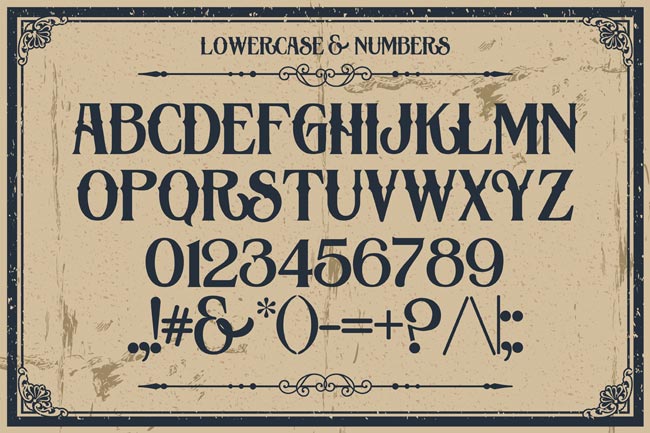
Лучшие ретро-шрифты для совершенствования вашего дизайнаDesigne-R
В этом посте мы представляем вам коллекцию высококачественных винтажных и лучших ретро-шрифтов, чтобы добавить нотку ностальгии в вашу работу.
При создании дизайна под влиянием искусства и культуры определенной эпохи лучше всего выбирать шрифты, которые визуально представляют этот период времени. Вот почему мы включили шрифты, вдохновленные эстетикой разных времен, будь то классический стиль начала 1900-х годов, стиль поп-арта 50-х и 60-х годов или фильмы, музыка и визуальные эффекты 70-х и 80-х годов. все!
Вы найдете сочетание различных стилей шрифтов, от шрифтов в стиле ретро до шрифтов кисти, жирных шрифтов с заглавными буквами до узких сжатых шрифтов, от монолинейных сценариев до многострочных шрифтов, пиксельных шрифтов, старинных шрифтов и многого другого. Эти шрифты идеально подходят для ваших проектов в винтажном и ретро-стиле, таких как флаеры, баннеры, приглашения, футболки, плакаты и дизайн логотипов.
В нашей коллекции есть как бесплатные, так и платные шрифты, и мы поместили их в разные разделы для удобства просмотра. В последнее время в моде ретро-дизайн 80-х и 90-х годов, ниже вы найдете довольно хороший выбор шрифтов, на которые повлияли стили шрифтов этих знаковых десятилетий.
Бесплатные винтажные и ретро шрифты
1. Streetwear – Бесплатный ретро Script шрифт
Streetwear – это смелый и стильный шрифт в стиле ретро, подходящий для логотипов, плакатов, брендинга, упаковки и футболок.
Он выглядит как шрифт 1960-х и 70-х годов, связанный с модой и спортом, уникальный и забавный одновременно.
Вы можете получить доступ к альтернативным персонажам Streetwear с помощью продвинутых программ OpenType, таких как Adobe Illustrator и InDesign. Дизайн студии Artimasa.
2. Sabo – Бесплатный Пиксельный шрифт
Sabo – это бесплатный 8-битный пиксельный шрифт, вдохновленный стилями пиксельных шрифтов 80-х годов. Доступно в двух стилях – «Заливка» и «Контур», которые можно комбинировать для создания трехмерного эффекта. Шрифт идеально подходит для оформления тематических ретро-аркад для игр, футболок и плакатов.
3. Bernier – Бесплатный винтажный шрифт
Винтажный шрифт Bernier – это шрифт, состоящий только из заглавных букв. У этого бесплатного шрифта есть 3 разных стиля (Regular, Distressed и Shade).
Он идеально подходит для винтажного значка, типографики в олдскульном стиле и логотипа.
4. Streamster – Бесплатный ретро шрифт 80-х
Streamster – это шрифт в стиле 80-х, разработанный Юсефом Хабчи. Шрифт идеально подходит для создания неоновых постеров и заголовков в стиле ретро. Streamster доступен для загрузки в формате TTF и бесплатен для использования в личных проектах.
5. Carosello – Винтажный шрифт
Carosello от Unio – это маркерный шрифт, вдохновленный винтажной рекламой. Создан с помощью настоящего маркера, чтобы сохранить и показать типичные рукописные недостатки.
Этот универсальный шрифт ручной работы идеально подходит для создания потрясающих цитат 1950-х годов, написанных вручную, вдохновляющих фраз и старинных дизайнов. Форматы шрифтов: OTF и TTF.
6.
Ansley Display – Бесплатный ретро шрифтAnsley Display – это шрифт в стиле ретро, созданный графическим дизайнером Кэди Джеско. Предназначен для заголовков и больших дисплеев.
Этот бесплатный шрифт доступен в 6 различных стилях: обычный, полужирный, черный, встроенный, контурный и светлый в виде файлов шрифтов TTF.
7. Good Times Regular – Бесплатный ретро шрифт
Good Times – это шрифт заголовков в стиле техно 1980-х годов, вдохновленный буквами, использовавшимися на автомобилях Pontiac примерно 1989–1994 годов. Равномерные линии веса и отдельные штрихи придают формам букв футуристический вид. Он выпускается в 15 стилях, и его обычный вес доступен для бесплатного скачивания в формате TTF. Разработано Typodermic Fonts.
8. West Side – шрифт 80-х
West Side от Artimasa Studio – это блочный шрифт ручной работы, вдохновленный дизайнами плакатов и иллюстраций ручной работы 1980-х годов.
9. Still Time – Бесплатный ретро шрифт
Still Time – бесплатный дисплейный шрифт в стиле рок-н-ролла 1980-х годов. Лицензия на шрифт разрешает бесплатное коммерческое использование. Разработанный Typodermic Fonts, Still Time доступен для загрузки в формате TTF.